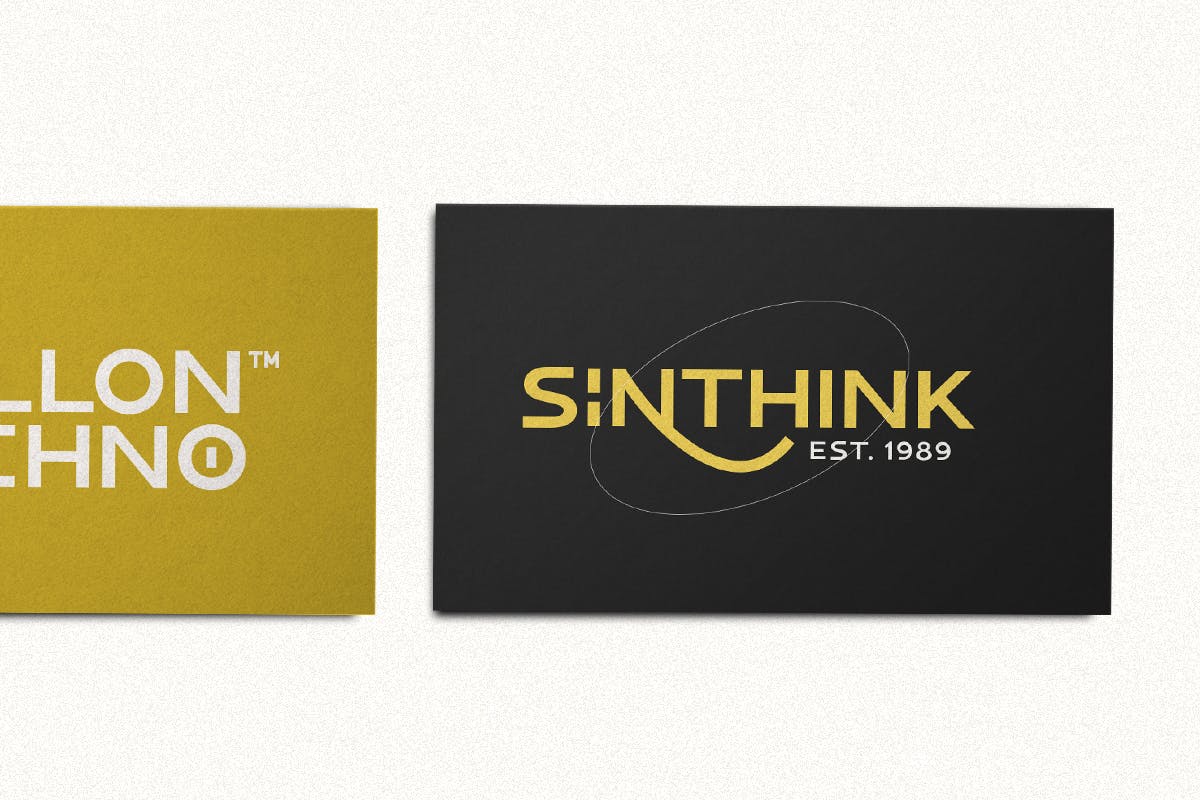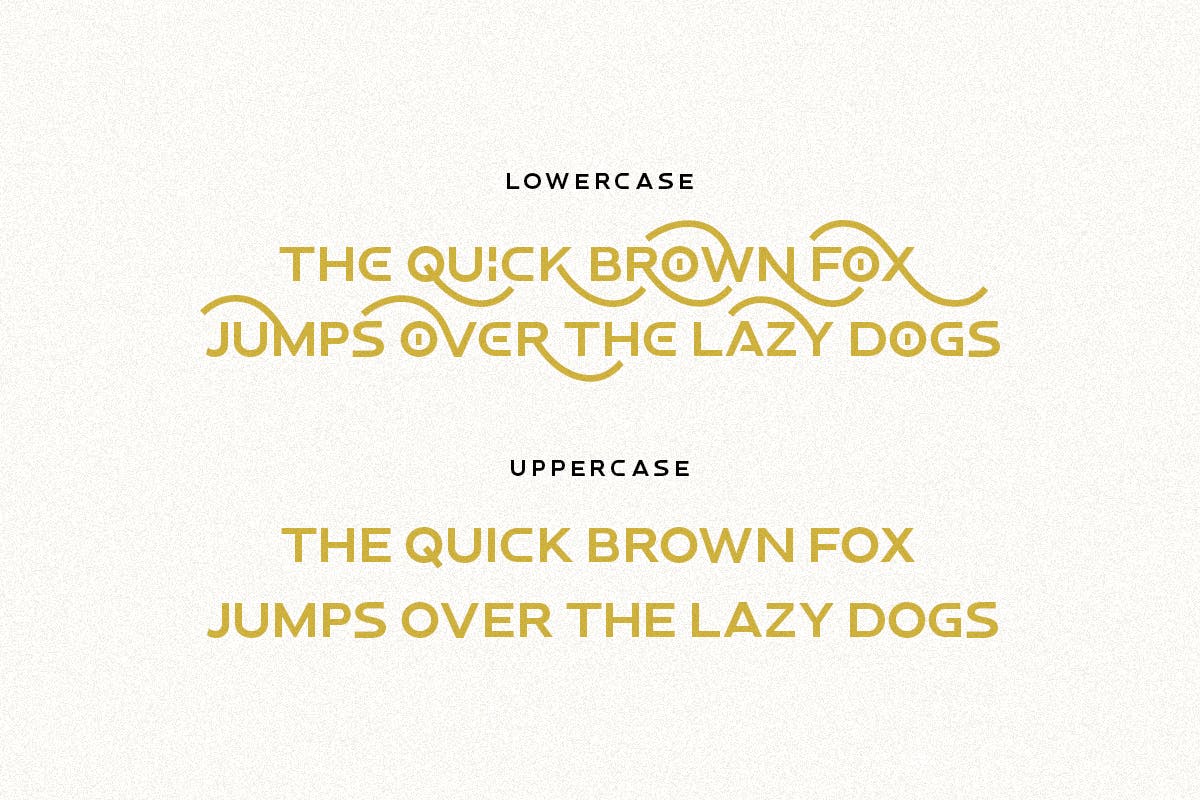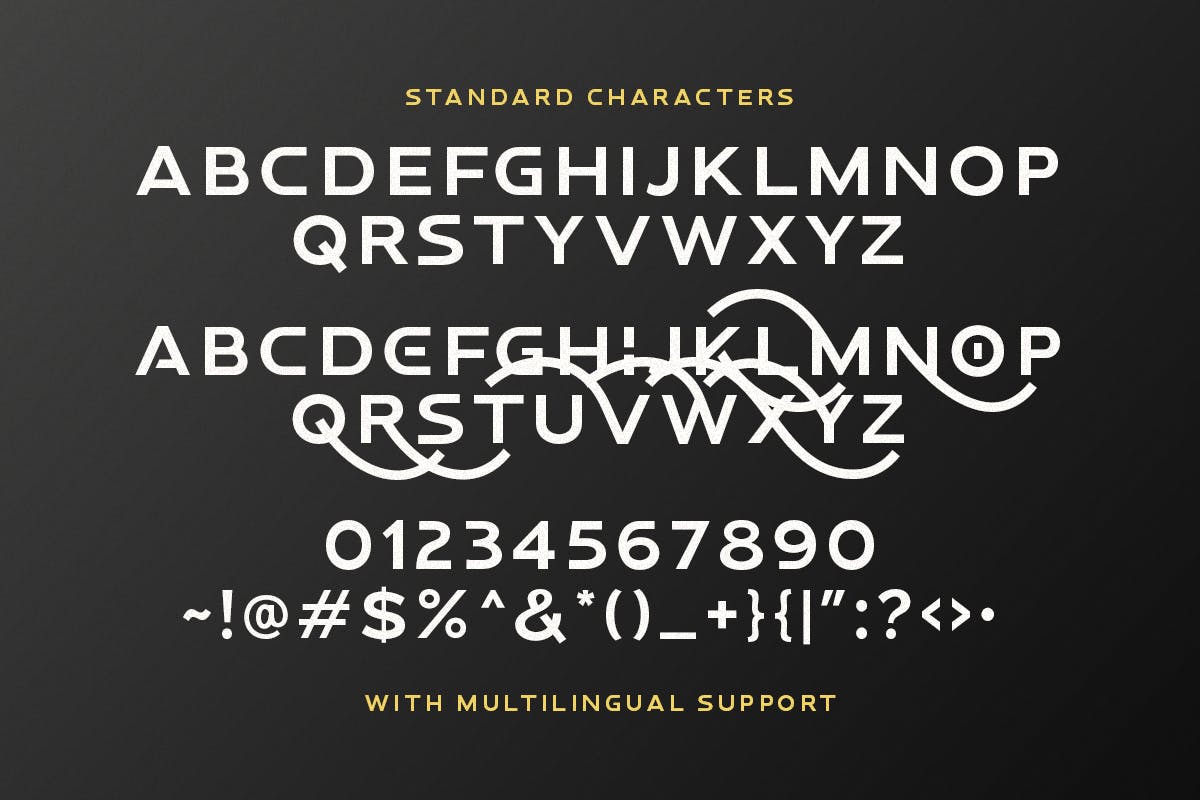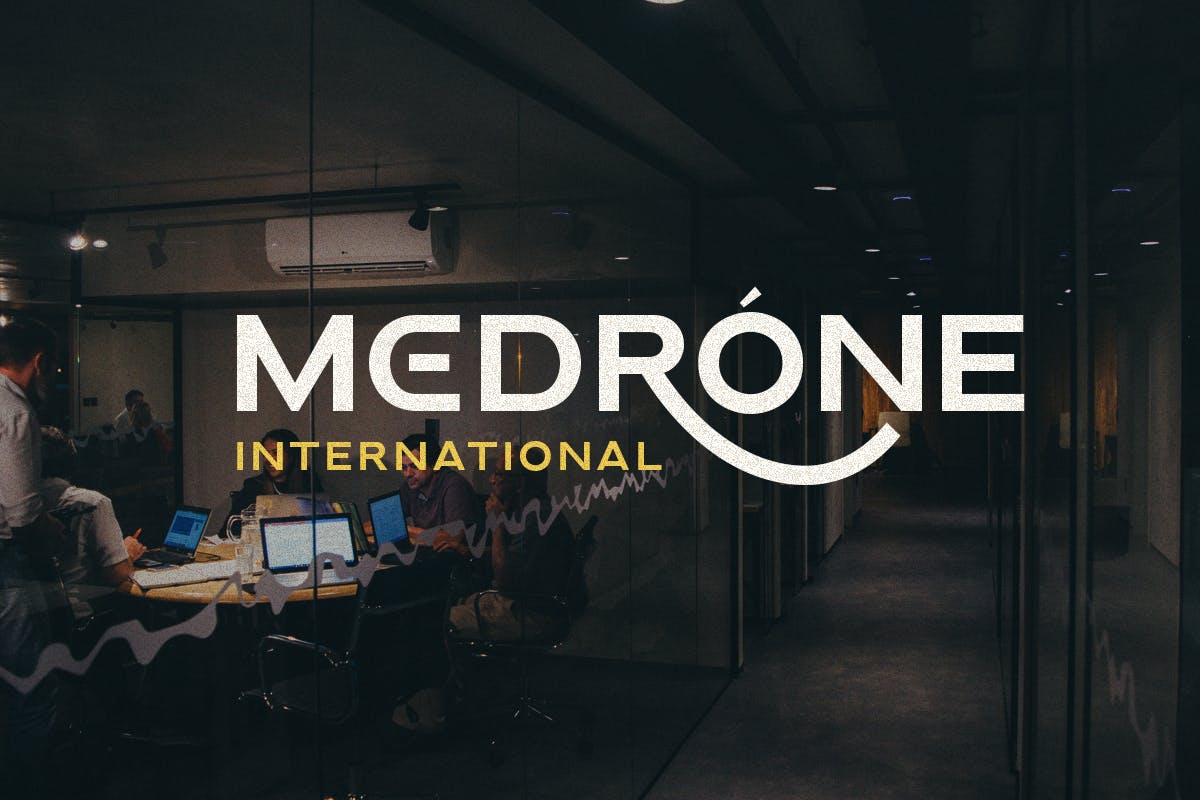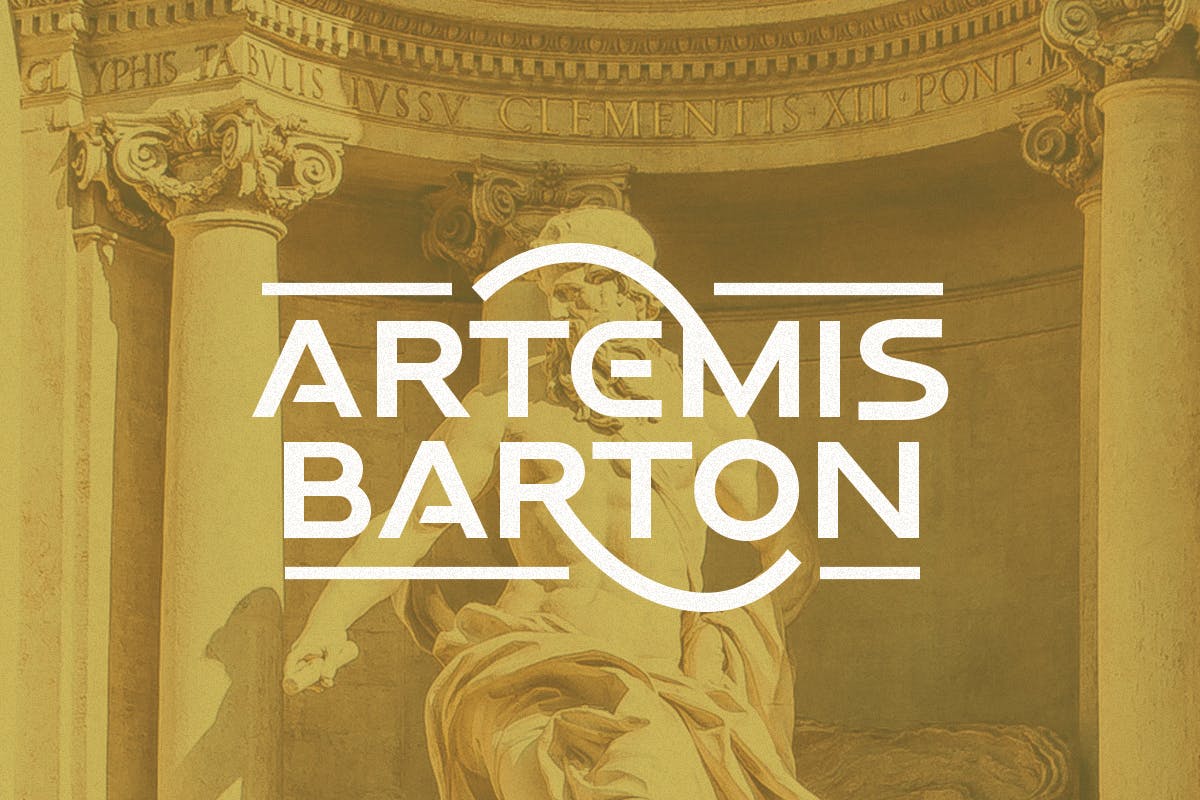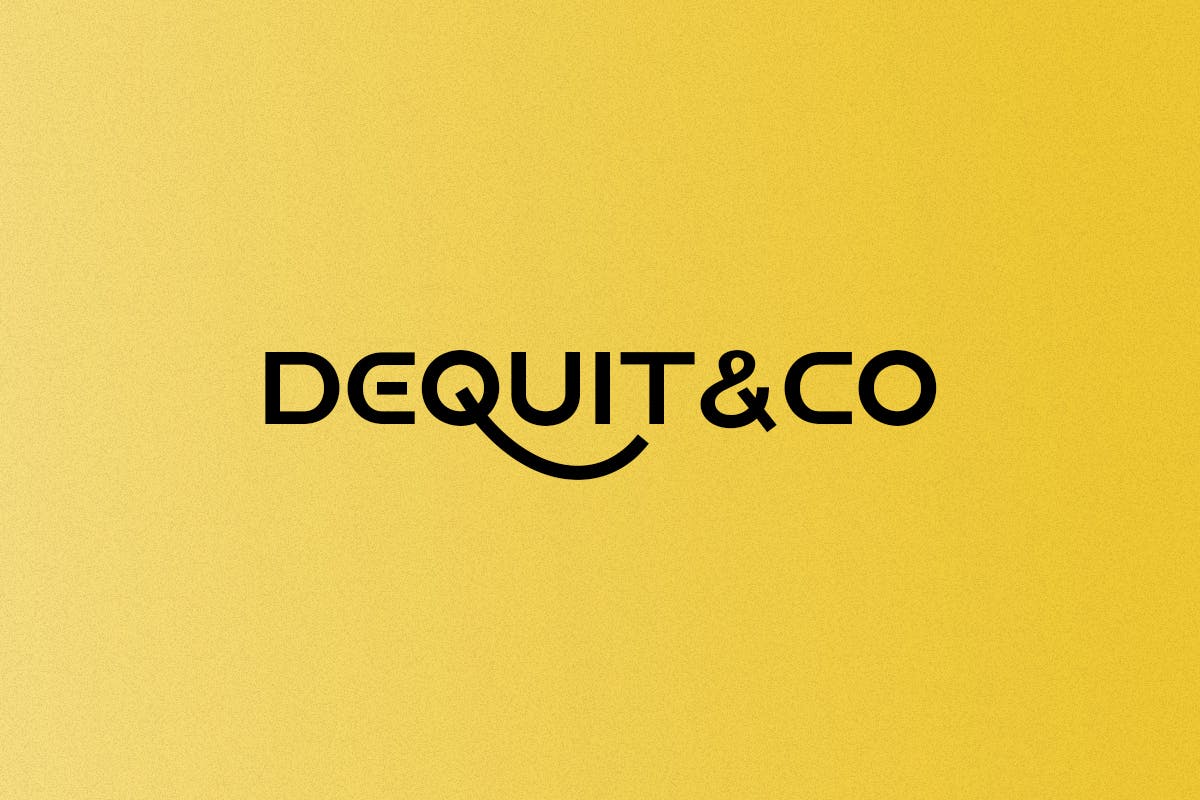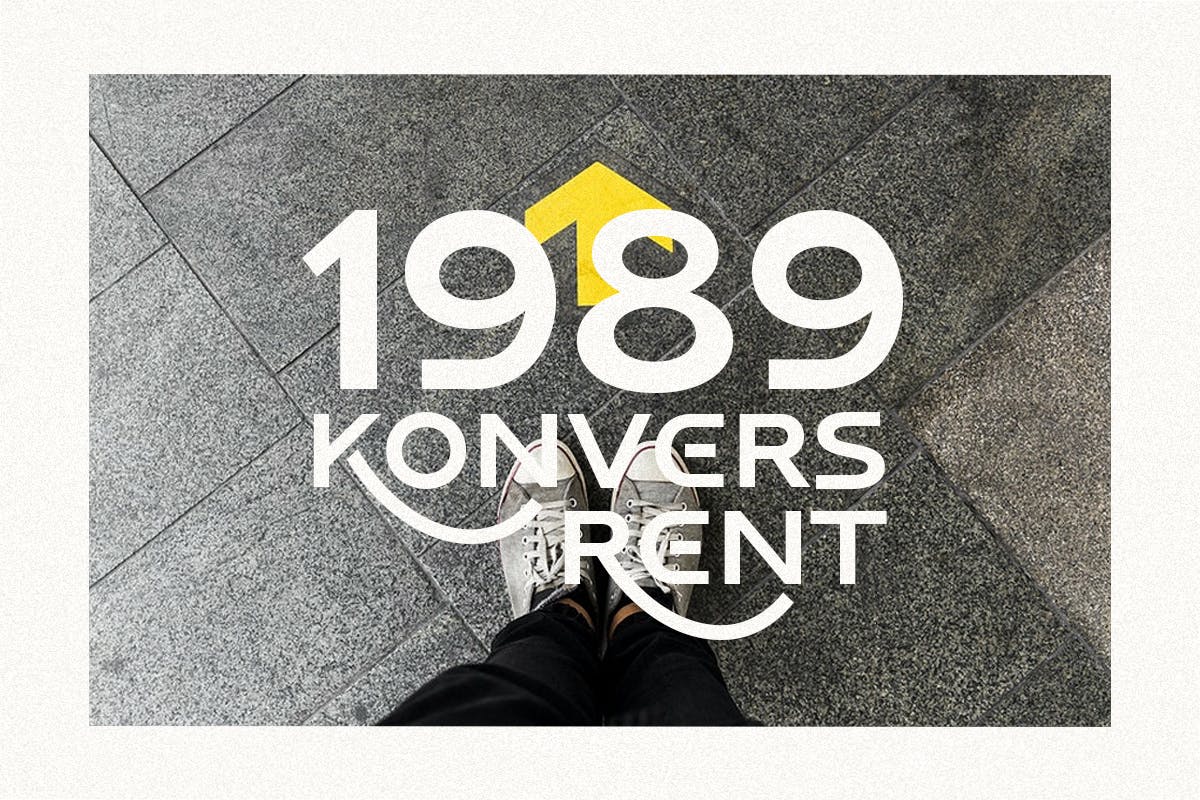
فونت Proxemic یک فونت بولد و بدون سر (sans) است که با حروف کوچک منحصر به فرد خود، لوگو و طراحی شما را به شکلی پیشرفته و مدرن جلوه میدهد. با استفاده از این حروف کوچک خاص، میتوانید تنها با چند مرحله ساده، لوگوی خود را جذابتر کنید. این فونت برای هر هدفی قابل استفاده است، بهویژه برای طراحی لوگوتایپ.
شما میتوانید حروف بزرگ و کوچک را با هم ترکیب کنید تا لوگوی خود را پیشرفتهتر کنید. علاوه بر این، این فونت شامل اعداد، نمادها و پشتیبانی از چند زبان است!